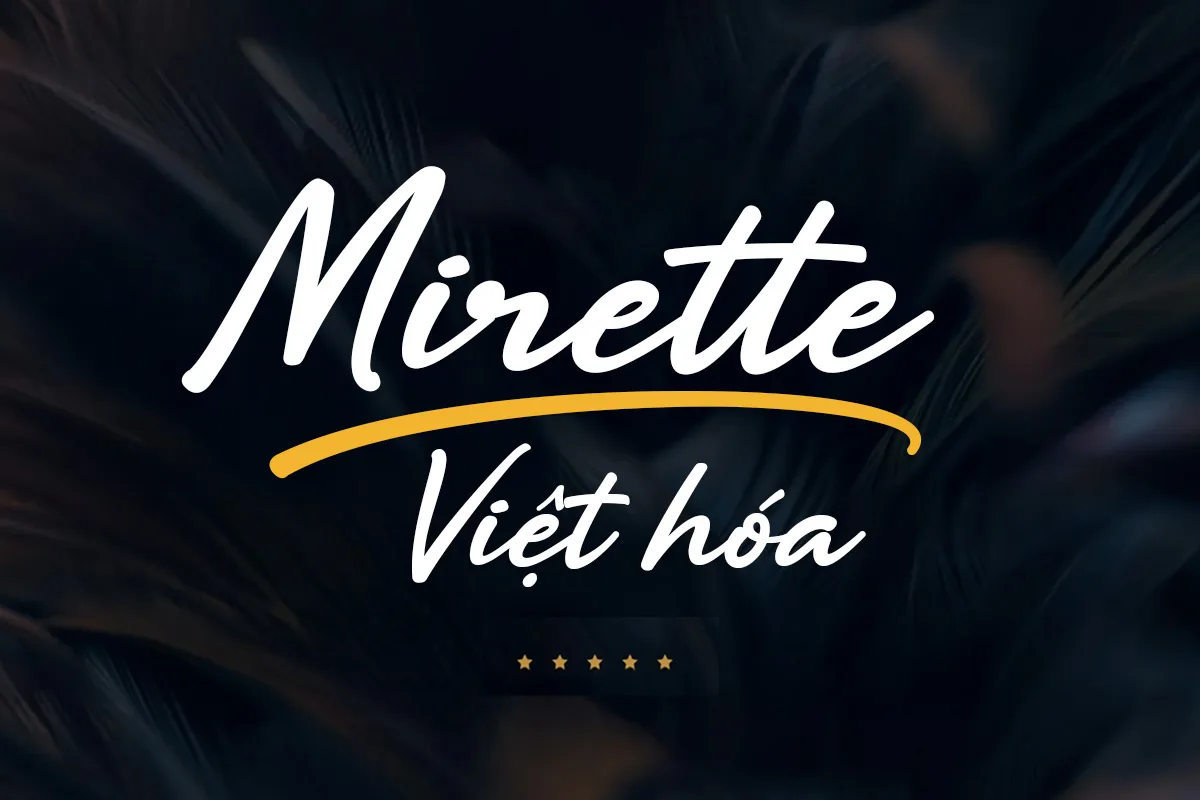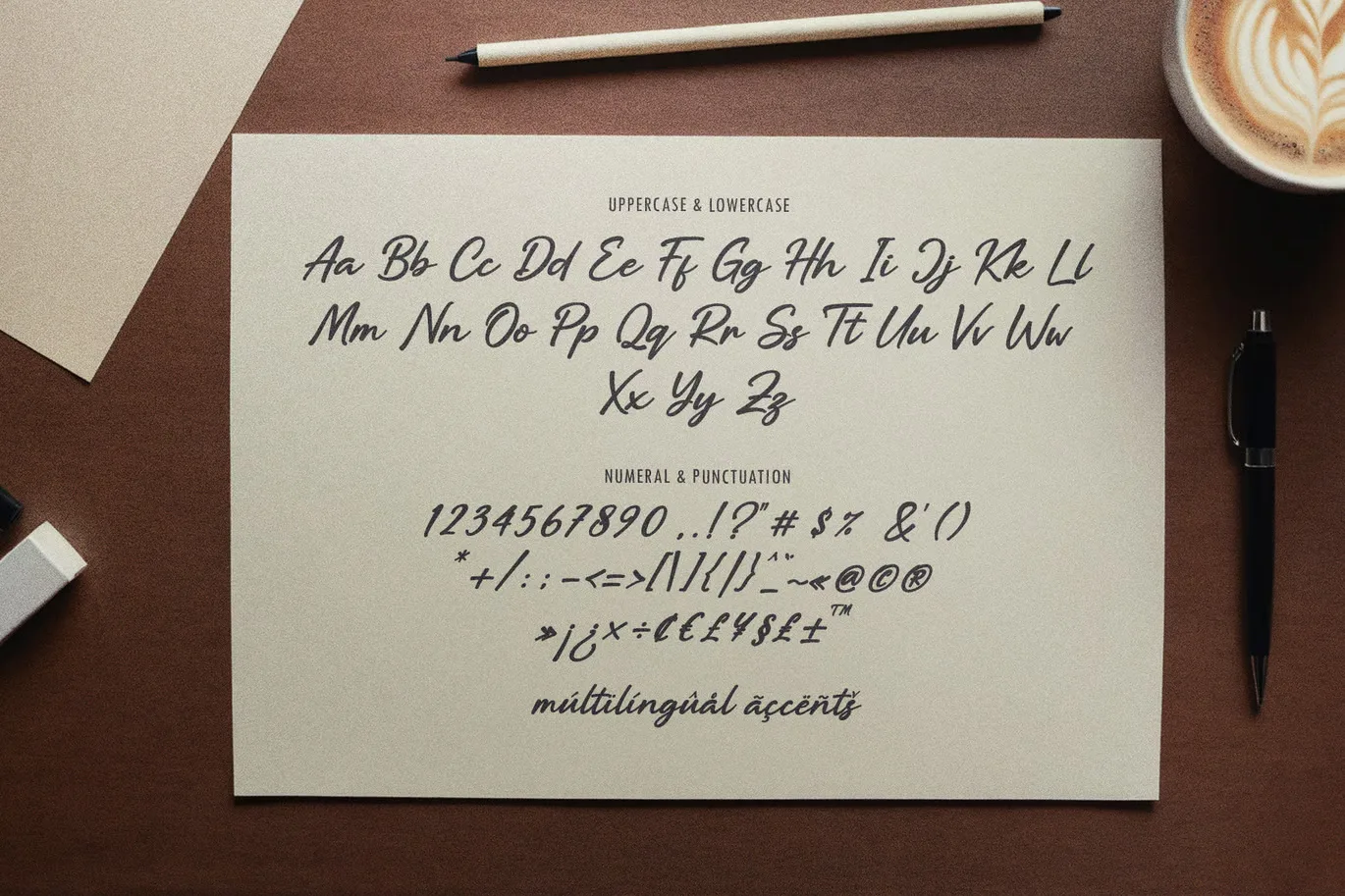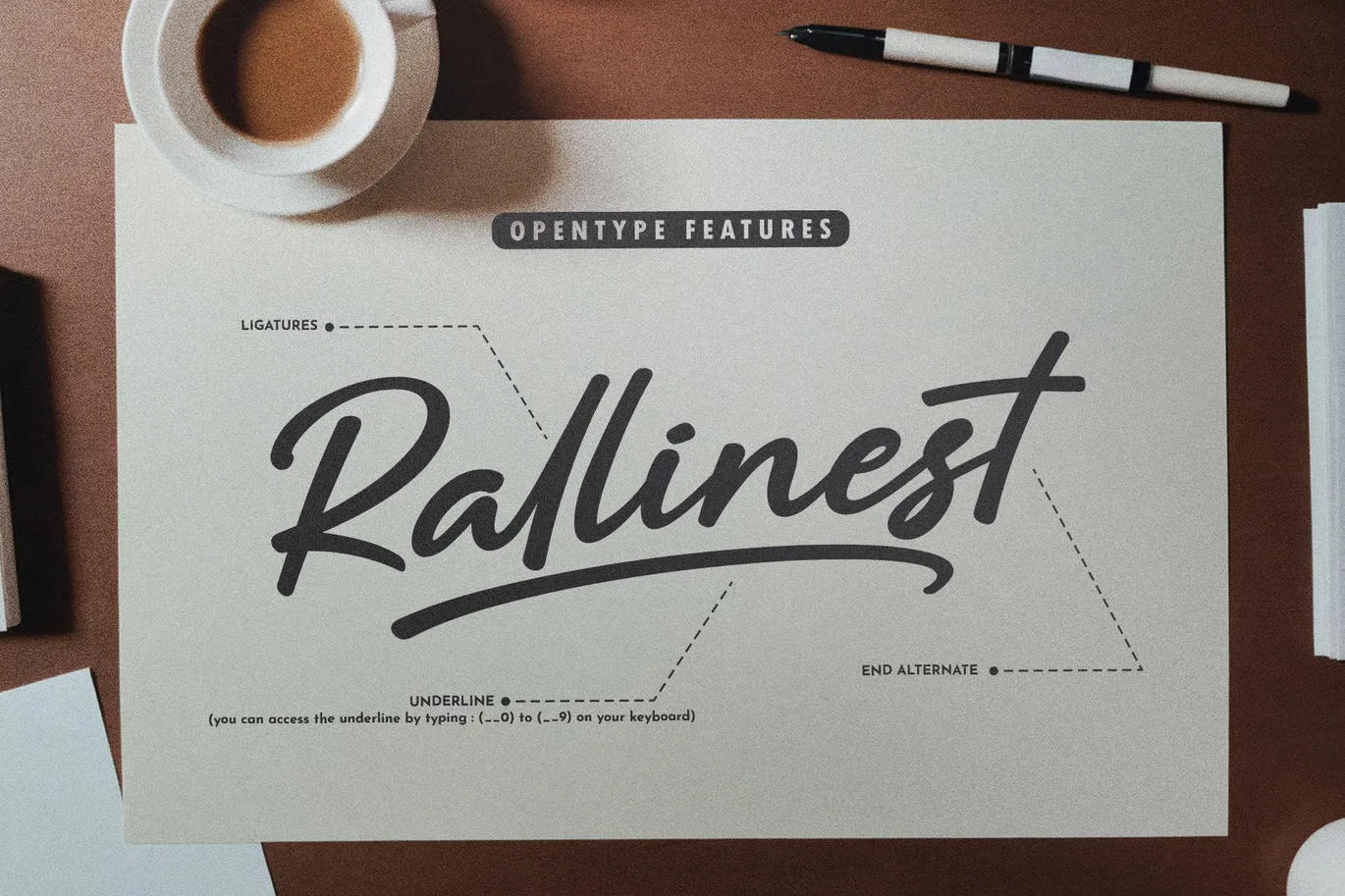
DVN Mirette Việt hóa – Font viết tay tinh tế, bay bổng và đầy cảm xúc
DVN Mirette Việt hóa là kiểu chữ viết tay mang hơi thở hiện đại kết hợp với sự duyên dáng cổ điển. Mỗi nét bút như một chuyển động nhẹ nhàng, mềm mại, gợi cảm giác như đang lướt tay trên giấy trong một buổi chiều yên tĩnh. Với thiết kế nghiêng thanh thoát, DVN Mirette đặc biệt phù hợp cho các dự án mang tính cá nhân, nghệ thuật như thiệp cưới, logo thời trang, bìa sách, trích dẫn truyền cảm hứng hoặc bài đăng mạng xã hội.
Bộ font đã được Việt hóa đầy đủ, hỗ trợ dấu tiếng Việt mượt mà và cân đối. Ngoài bảng chữ cái cơ bản, DVN Mirette còn bao gồm bộ ký tự đặc biệt, số và đa dạng ký hiệu hỗ trợ đa ngôn ngữ. Đây là lựa chọn lý tưởng cho những ai yêu thích sự mềm mại, tinh tế nhưng vẫn giữ được nét hiện đại trong từng thiết kế.